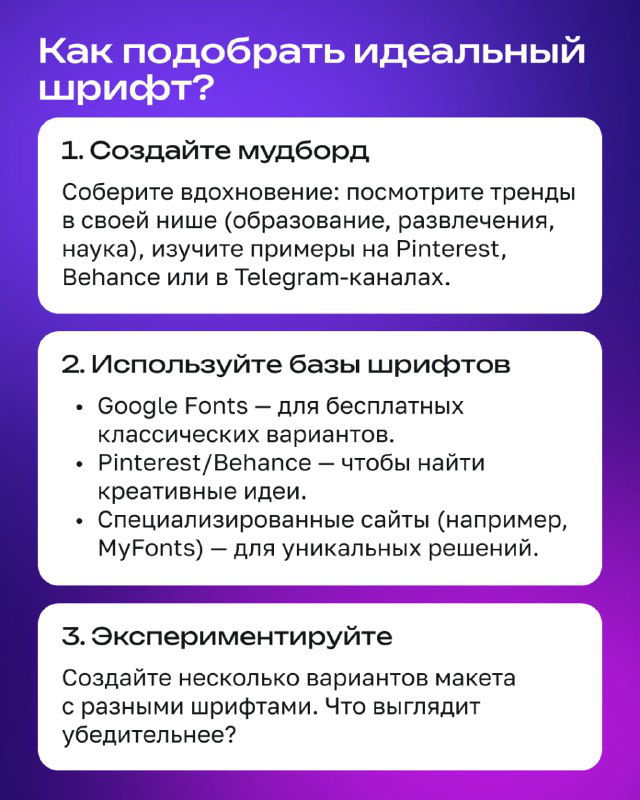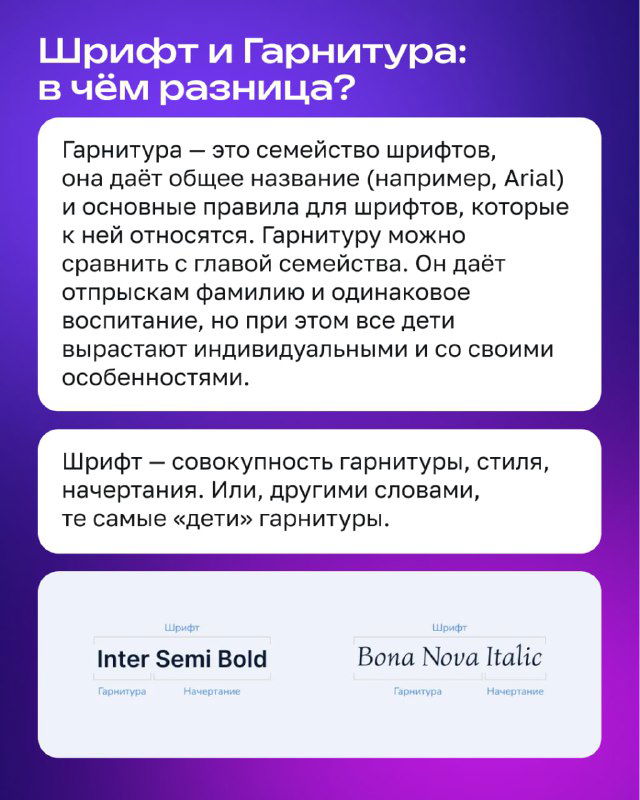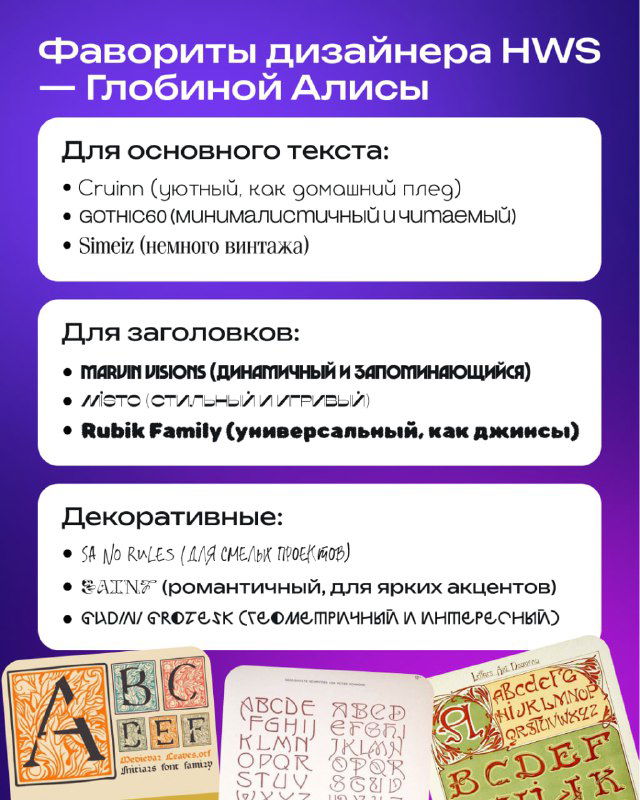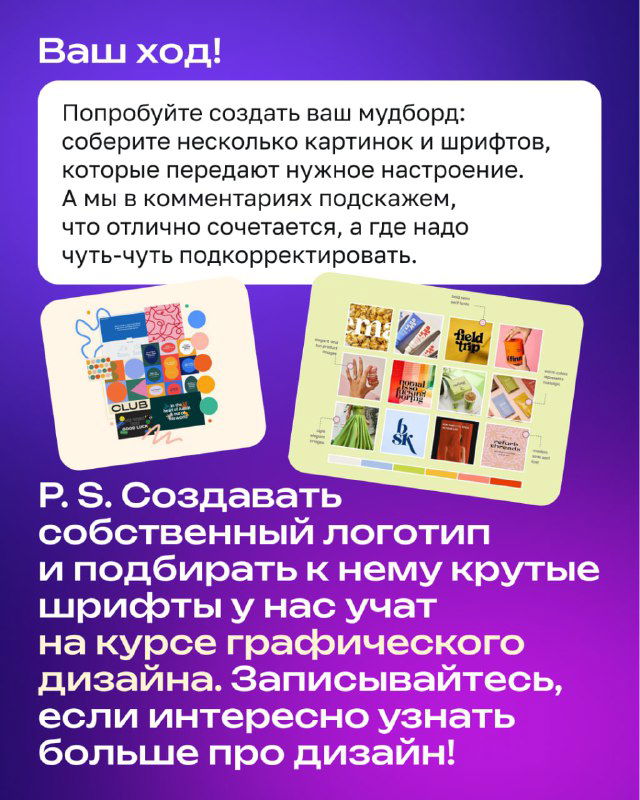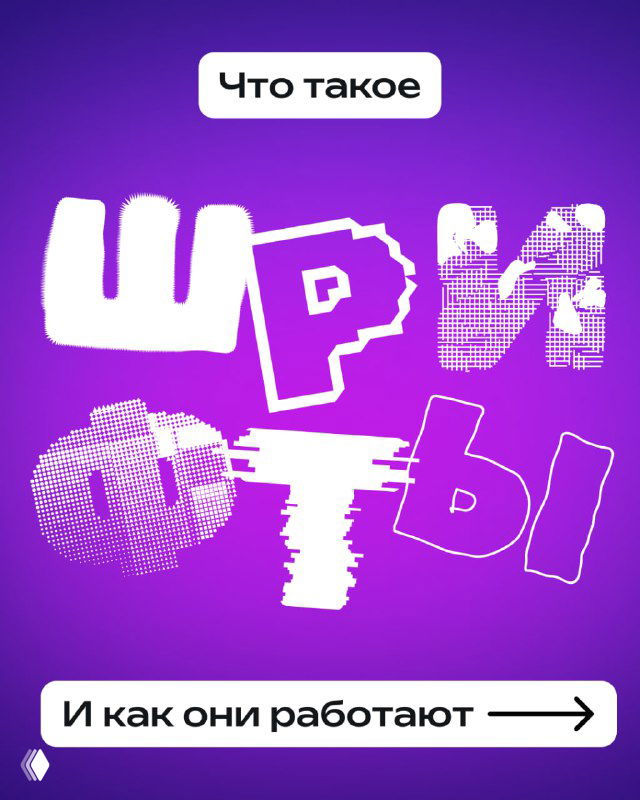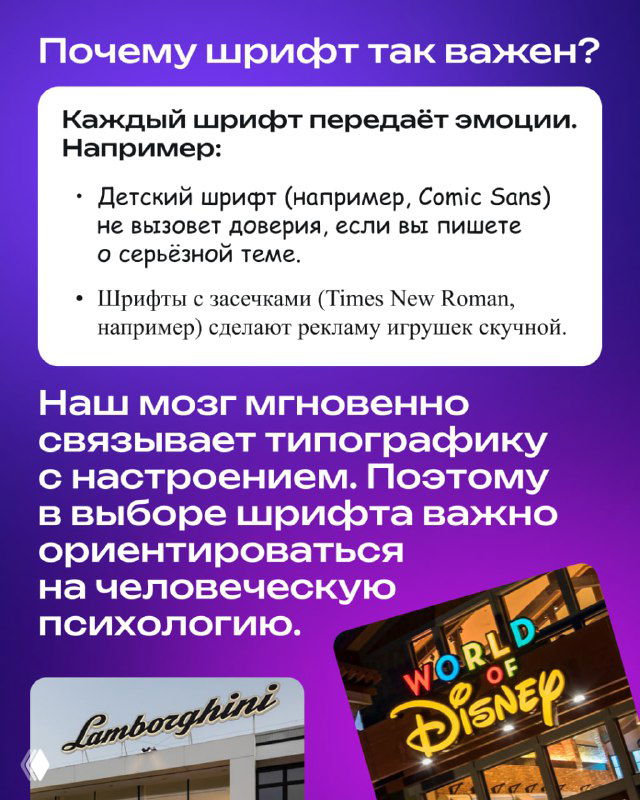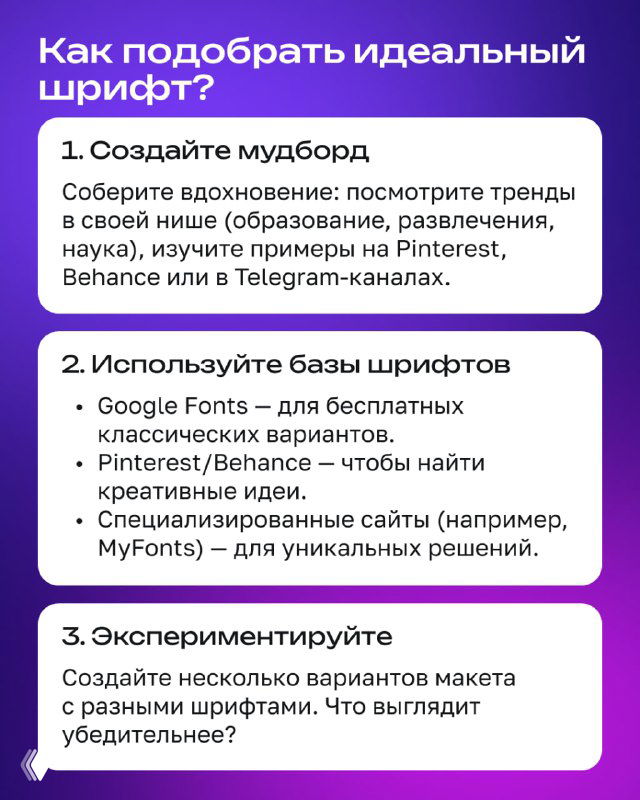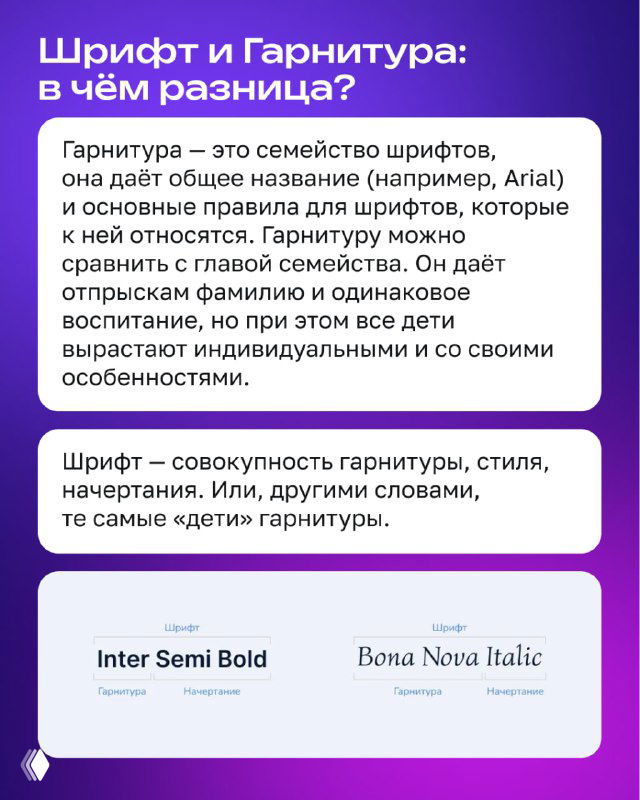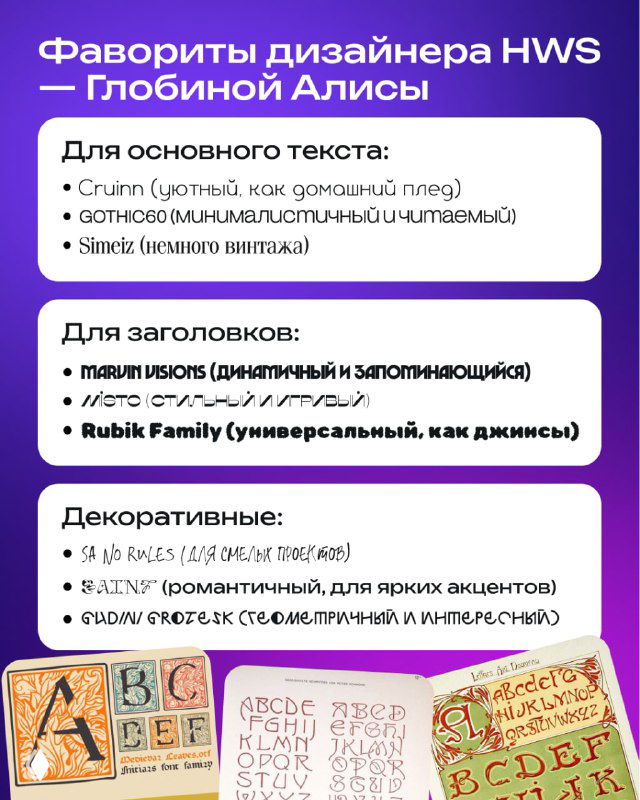
Почему шрифт важен и как его выбрать
Вы когда-нибудь задумывались, почему важен не только смысл текста, но и его «одежда» — шрифт? Оказывается, половина успеха коммерческого или делового сообщения зависит от оформления.
Сегодня поговорим о том, как шрифты «разговаривают» с нами и как их правильно выбирать.
Обложка: крупный надпись «Что такое шрифты» на пурпурном фоне, стилизованная типографика и графические элементы, превью карточек по шрифтам.
Карточка 1: что такое шрифты — обложка набора карточек
Слайд с заголовком о важности шрифта: примеры детского шрифта и шрифта с засечками, коллаж с логотипами для контекста.
Карточка 2: почему шрифт важен — примеры и эмоциональная составляющая
Слайд с рекомендациями: как подобрать идеальный шрифт — мудборд, Google Fonts, Pinterest и экспериментальные варианты макета.
Карточка 3: как подобрать идеальный шрифт — шаги и источники вдохновения
Слайд объясняет разницу между шрифтом и гарнитурой, с примерами названий гарнитур и образцами начертаний на светлом фоне.
Карточка 4: шрифт и гарнитура — в чём разница
Слайд с фаворитами дизайнера: списки шрифтов для основного текста, заголовков и декоративных решений с примерами использования.
Карточка 5: фавориты дизайнера для разных задач